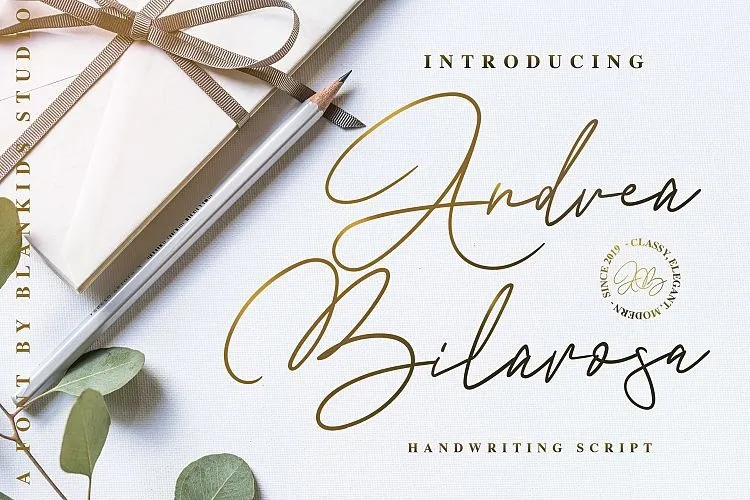
Andrea Belarosa Handwritten Font – Download Grátis
Esta font ‘Andrea Belarosa Handwritten’ é criada para projetos que requerem uma escrita elegante e moderna. Ela é perfeita para uso em diversos tipos de trabalho como cartazes, convites sociais, logomarcas, casamentos e design gráfico. Este belo tipo foi desenvolvido por 24Design, inspirado nas marcas inconfundíveis da vida cotidiana. Obrigado a Blankids por compartilhar essa font perfeita para tornar seus projetos ainda mais incríveis. Seja para criar um convite de casamento sofisticado ou uma identidade visual que ressoe com sua personalidade, Andrea Belarosa Handwritten é um excelente escolha. Não perca esta oportunidade de dar um toque único e elegante aos seus projetos!